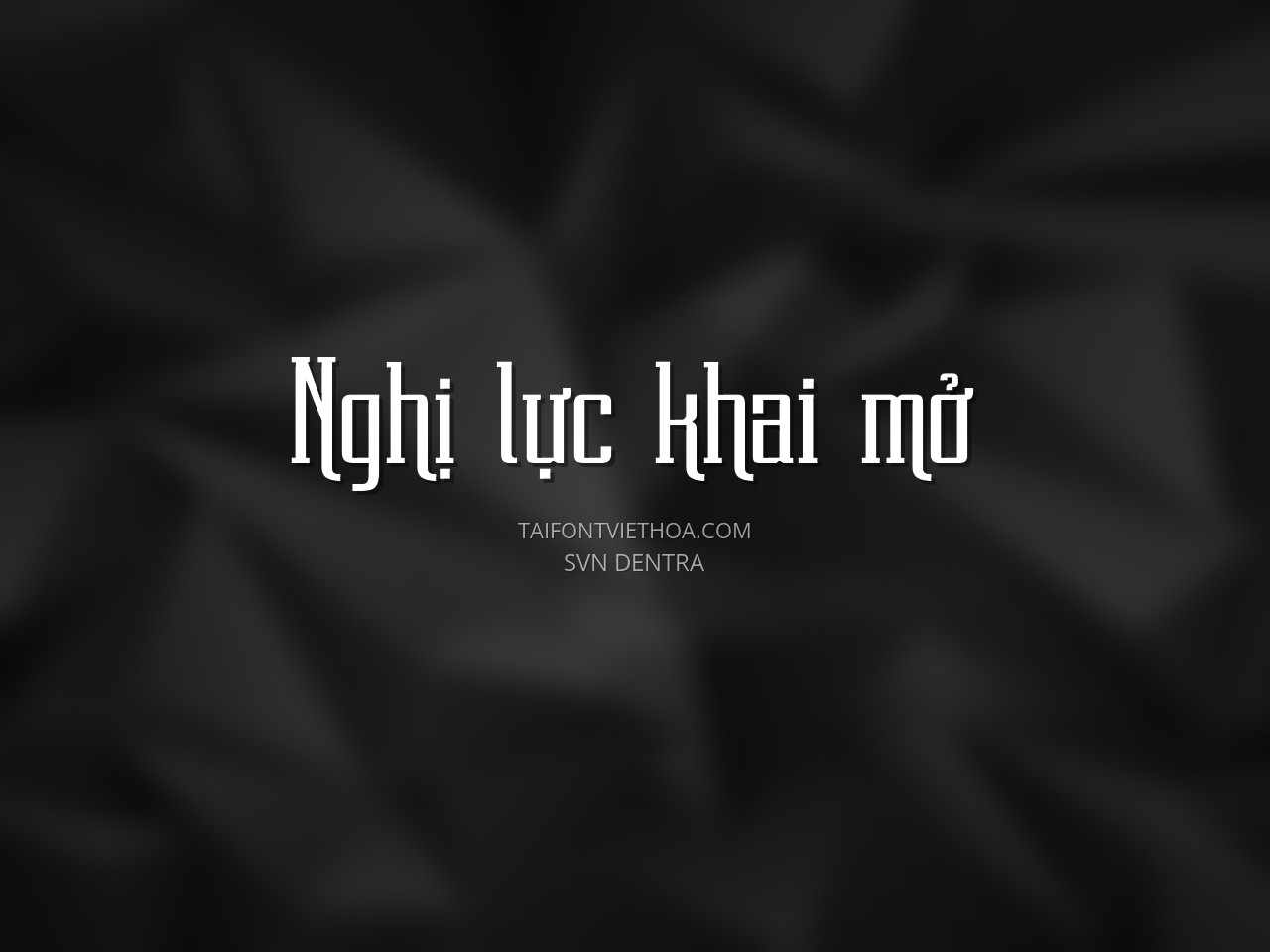
Font việt hóa SVN Dentra
Tác giả Font: Ferdiansyah_Ijemrockart
Giới thiệu về font SVN Dentra – Kiểu chữ serif thanh lịch, cổ điển và trang trọng
SVN Dentra là phiên bản Việt hóa của font Dentra – một kiểu chữ serif mang phong cách cổ điển, thanh lịch và rất trang trọng. Font được thiết kế với các nét chữ sắc nét, cân đối và tinh tế, phù hợp cho các dự án thiết kế thương hiệu, in ấn và truyền thông cao cấp.
Thiết kế serif tinh tế – Ứng dụng rộng rãi trong thương hiệu và xuất bản
SVN Dentra sở hữu cấu trúc serif với các nét chữ thanh mảnh, đường cong uyển chuyển và độ tương phản hài hòa. Font phù hợp cho đoạn văn bản dài và tiêu đề, giúp tăng tính thẩm mỹ và sự chuyên nghiệp cho thiết kế. Phong cách của Dentra mang đến sự trang nhã và bền vững cho mọi sản phẩm thiết kế.
Ứng dụng lý tưởng: thiết kế nhận diện thương hiệu, bìa sách, tạp chí, brochure, thư mời, danh thiếp và các ấn phẩm quảng cáo cao cấp. Ngành nghề phù hợp: thời trang, mỹ phẩm, nội thất, giáo dục, xuất bản và các thương hiệu định vị theo phong cách thanh lịch, cổ điển.